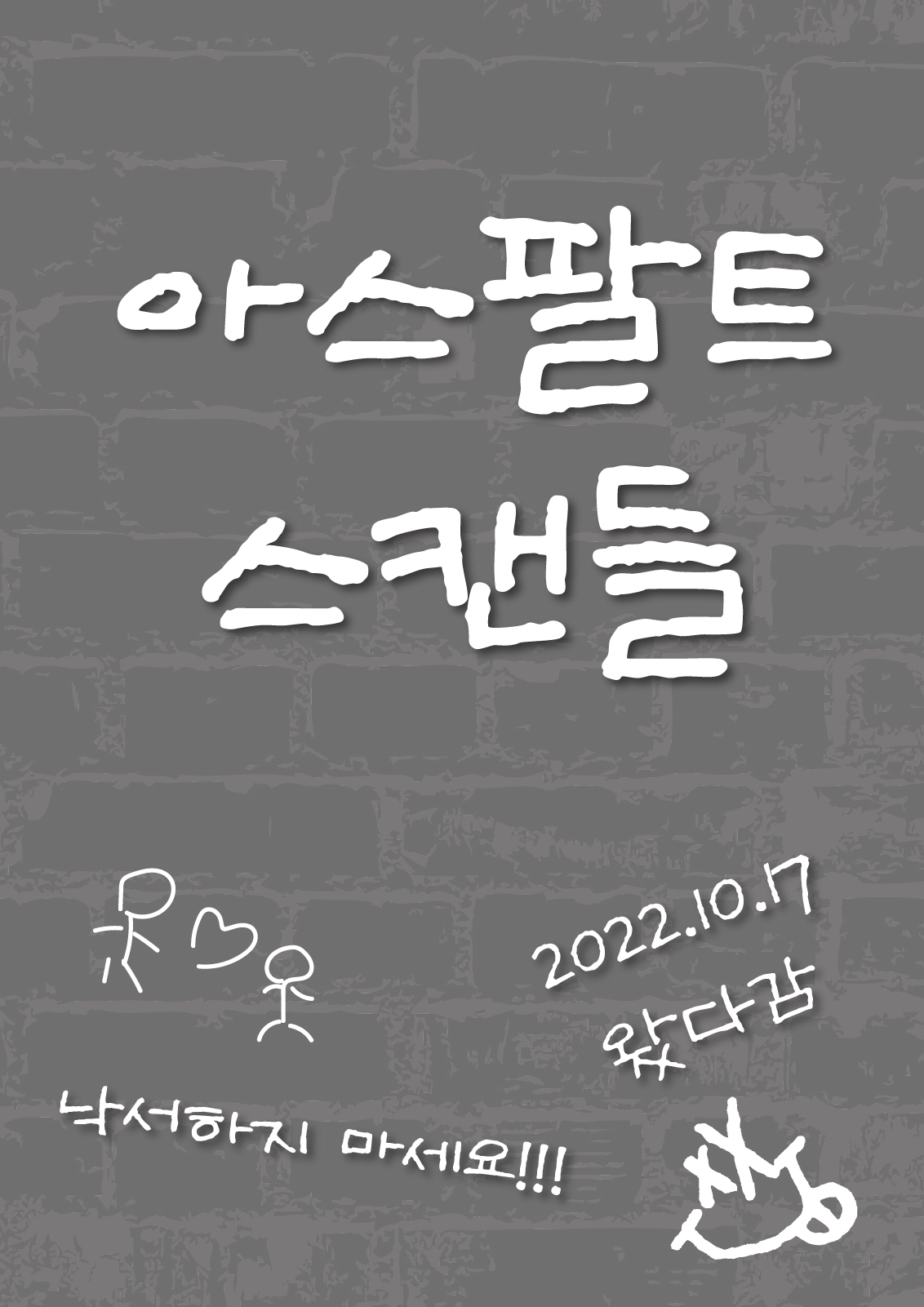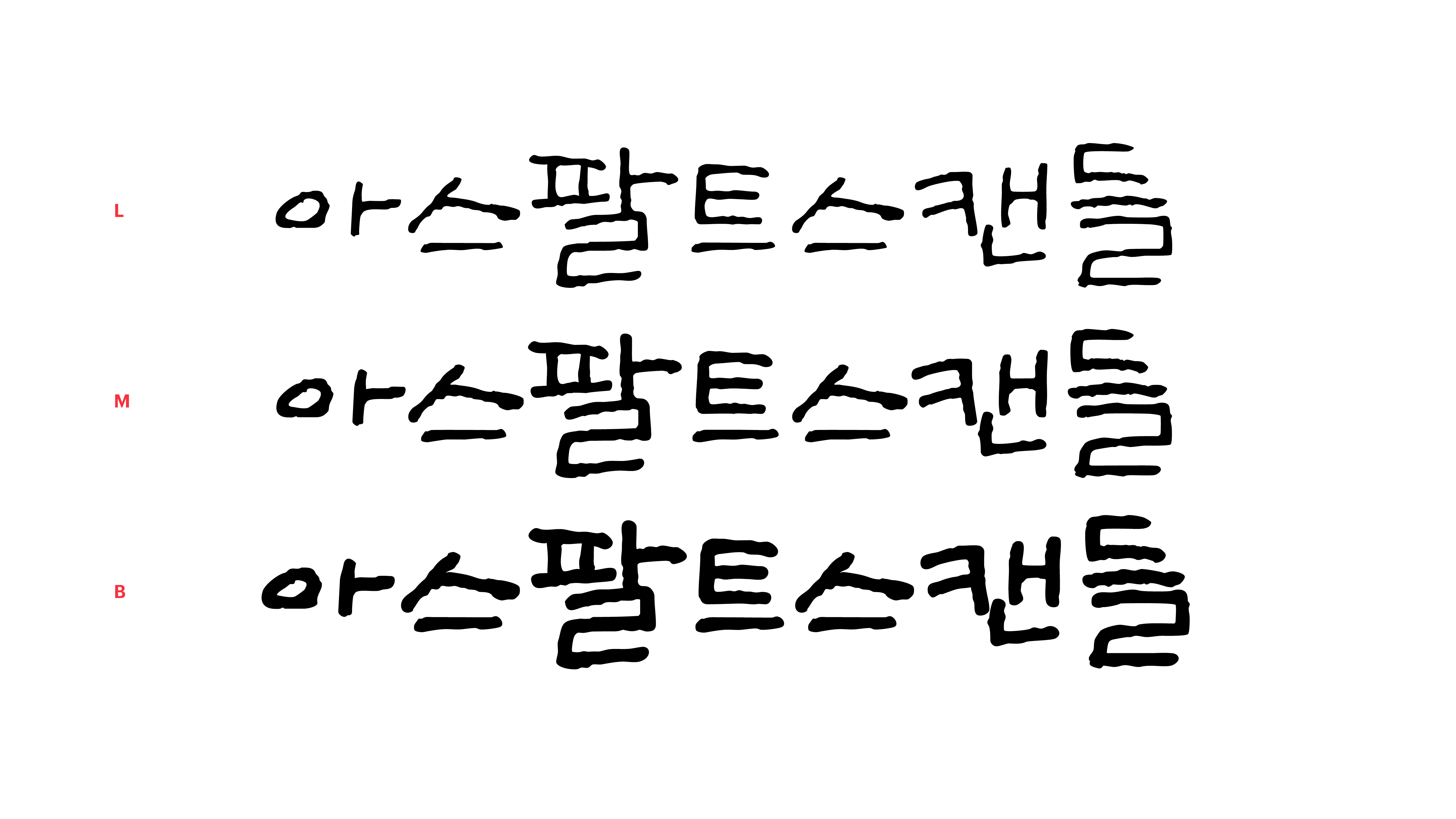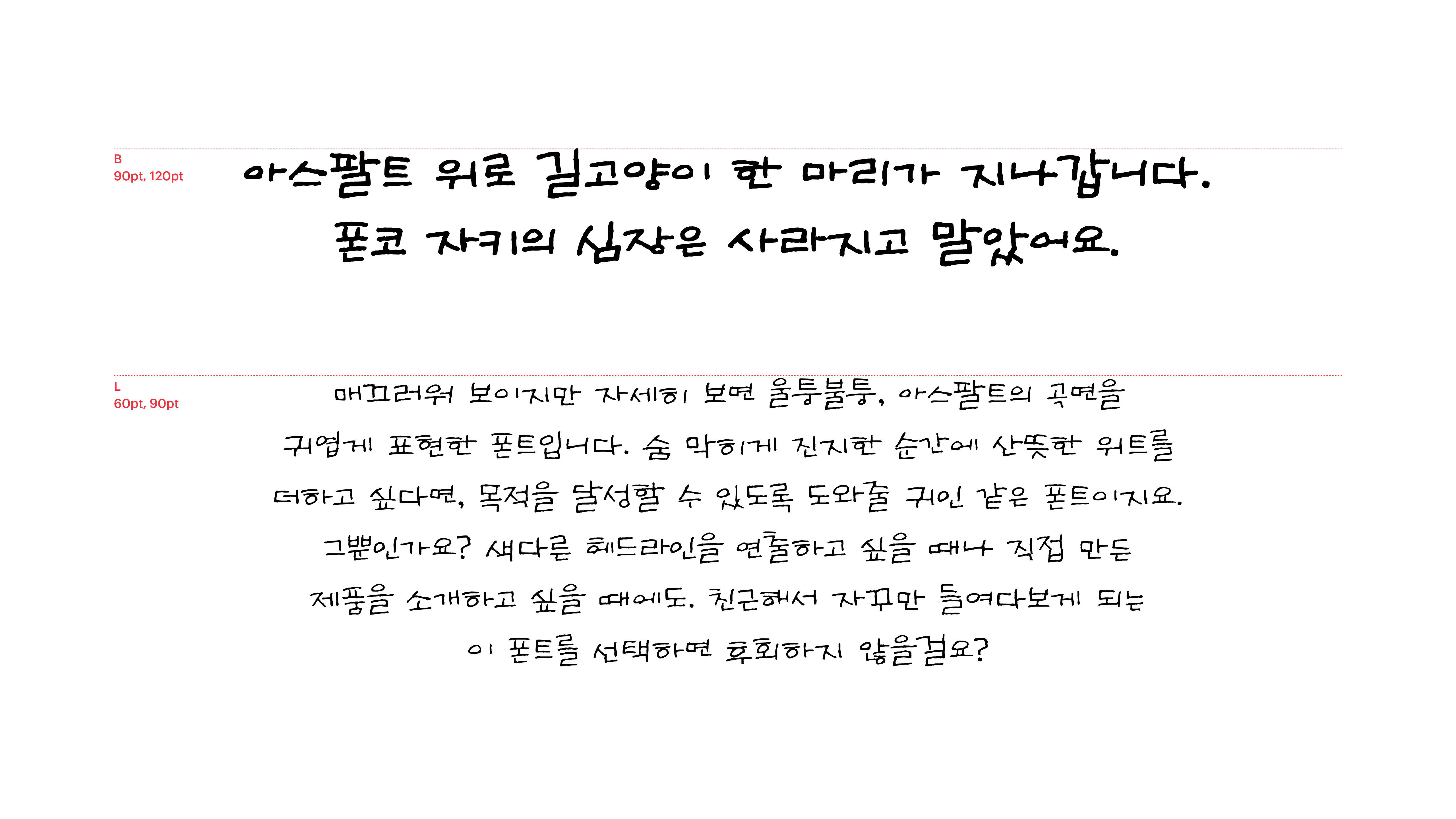
매끄러워 보이지만 자세히 보면 울퉁불퉁, 아스팔트의 곡면을 귀엽게 표현한 폰트입니다. 숨 막히게 진지한 순간에 산뜻한 위트를 더하고 싶다면, 목적을 달성할 수 있도록 도와줄 귀인 같은 폰트이지요. 그뿐인가요? 색다른 헤드라인을 연출하고 싶을 때나 직접 만든 제품을 소개하고 싶을 때에도. 친근해서 자꾸만 들여다보게 되는 이 폰트를 선택하면 후회하지 않을걸요?
Yoon DS아스팔트스캔들